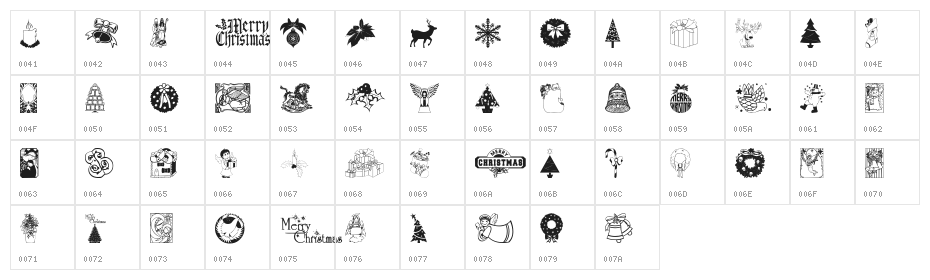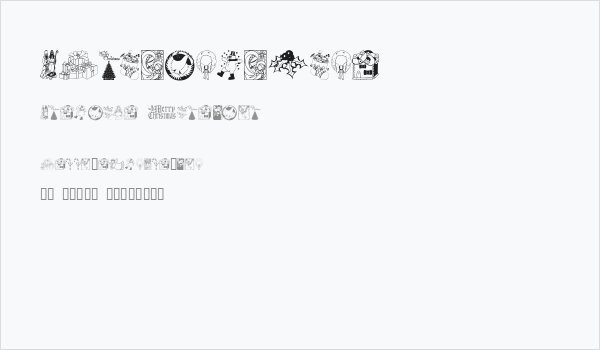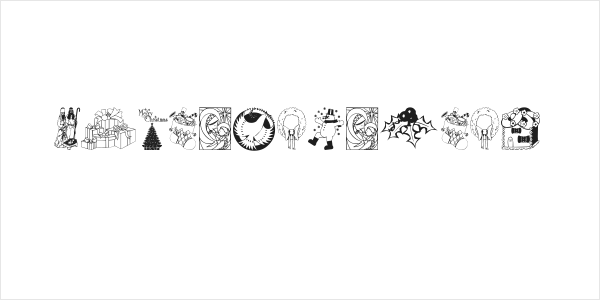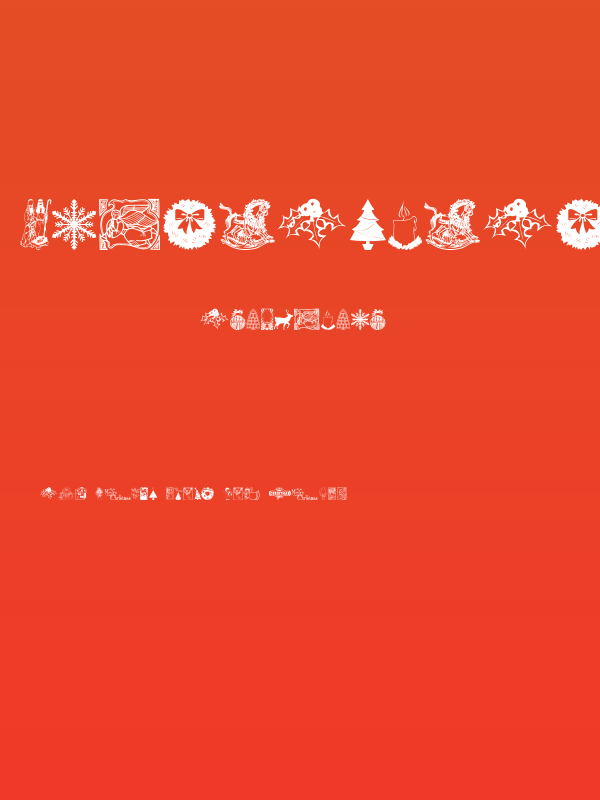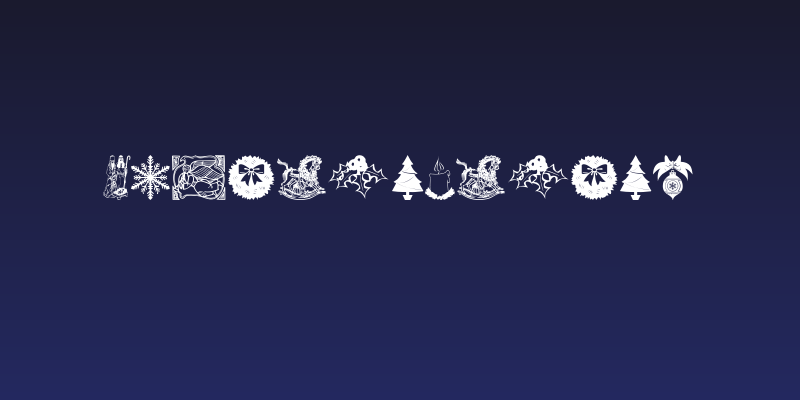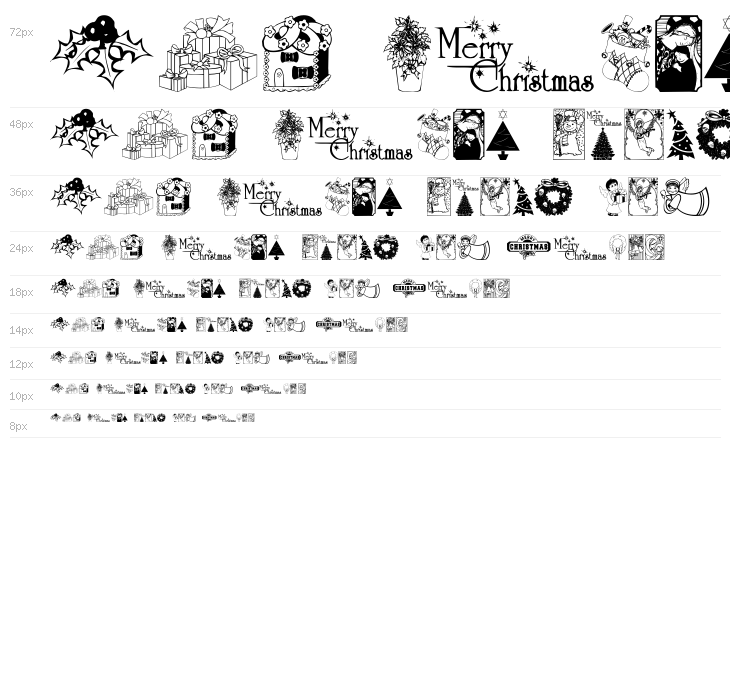
ChristmasTime Font
| Caso de uso | Decorative graphics for holiday themes. |
| Proyectos propuestos | These graphics could be used for holiday cards, festive decorations, or seasonal marketing materials. |